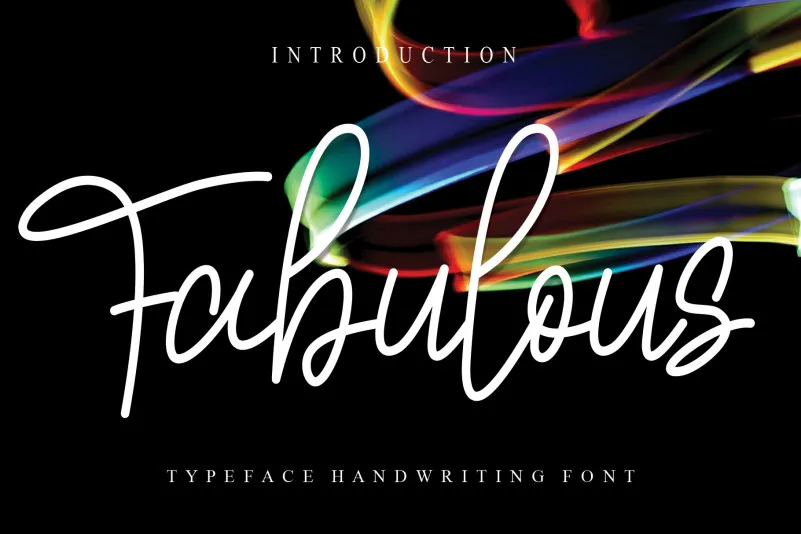
A ‘Fabulous Handwritten Font’ é uma criação única que oferece à sua obra uma aparência autêntica e envolvente, ideal para quem busca dar vida a suas mensagens de forma elegante e sofisticada. Desenvolvida pelo designer criativo da CreativeLetter, essa fonte traz um toque especial ao seu trabalho, tornando-o ainda mais expressivo e inesquecível. Ela é perfeita para designers que desejam dar um salto acima na apresentação de seus projetos, transformando simples textos em verdadeiros trabalhos de arte com sua escrita autêntica e vibrante. Não importa se você está criando material editorial ou design gráfico, a ‘Fabulous Handwritten Font’ oferece uma ferramenta poderosa para tornar seu conteúdo ainda mais cativante e memorável.